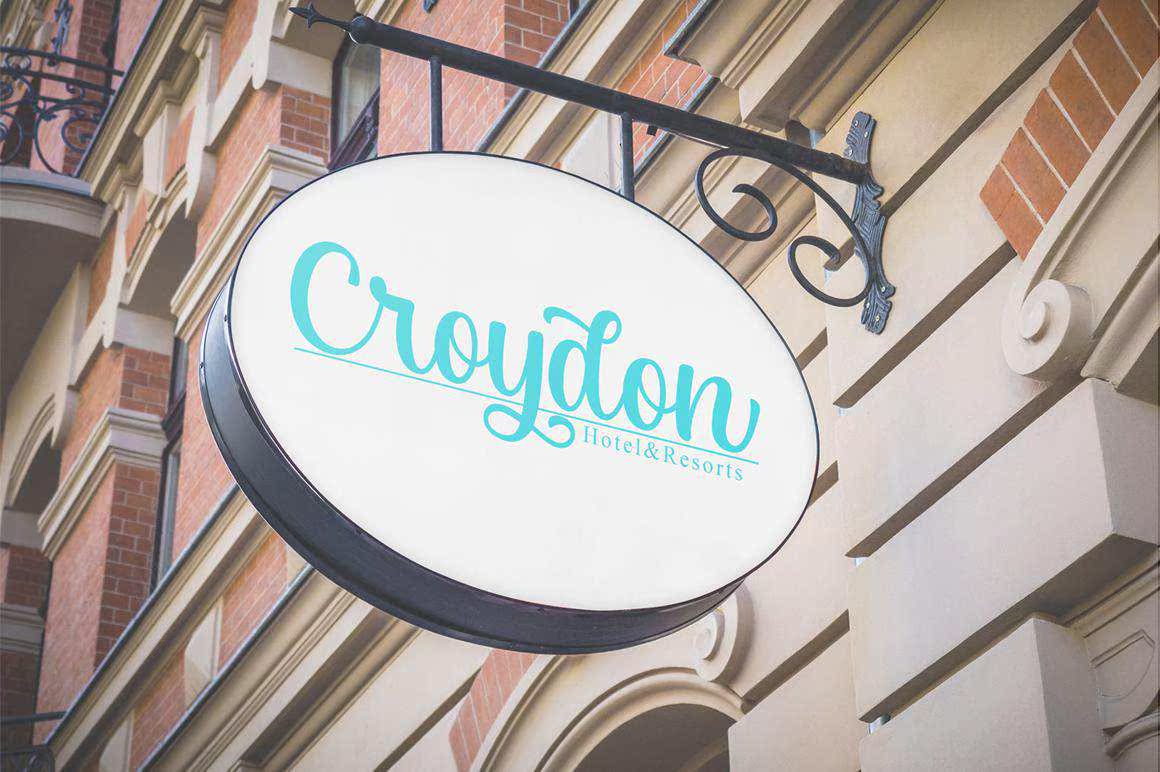
Mayonese是一款风格独特的现代手写字体,具有丰富的CASE字体功能。并添加了一些连字,使文字看起来更整洁、更美观。此字母可用于公司。例如,将文字用于徽标、名片、名片、信头、标签、小册子、水印、,可以打印成衬衫。此字母具有以下特征。Mayonese是一款现代手写字体,具有更丰富的CASE字体特征。并添加了一些连字,使字体看起来更整洁、更美观。此字母可用于公司。例如用于徽标、名片、名片、信头、标签、宣传册、水印、,可以打印Fort-shirts。此字母具有以下特征。